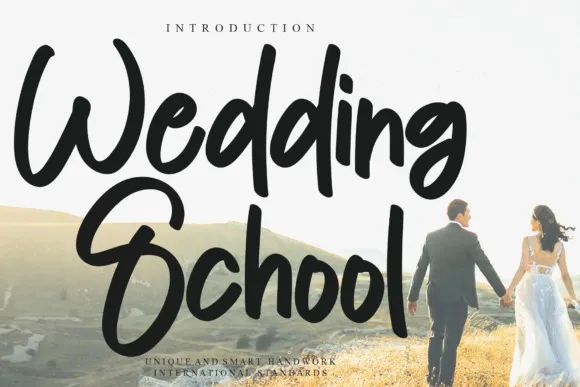
A fonte Wedding School é uma escolha perfeita para aqueles que desejam adicionar um toque autêntico aos projetos digitais. Desenvolvida por andikastudio, esta fonte escrita a mão oferece um visual simples e fluente, ideal para projetos variados como editoriais de casamento, festas infantis, lembranças ou até mesmo cards personalizados. Com seu estilo leve e versátil, essa font irá dar um toque divertido e descontraído a qualquer projeto que você esteja criando. Ideal tanto para profissionais quanto para amantes da design gráfico, esta é uma excelente opção para aqueles que desejam incorporar personalidade ao seu trabalho, em harmonia com o tema de casamento ou festas.